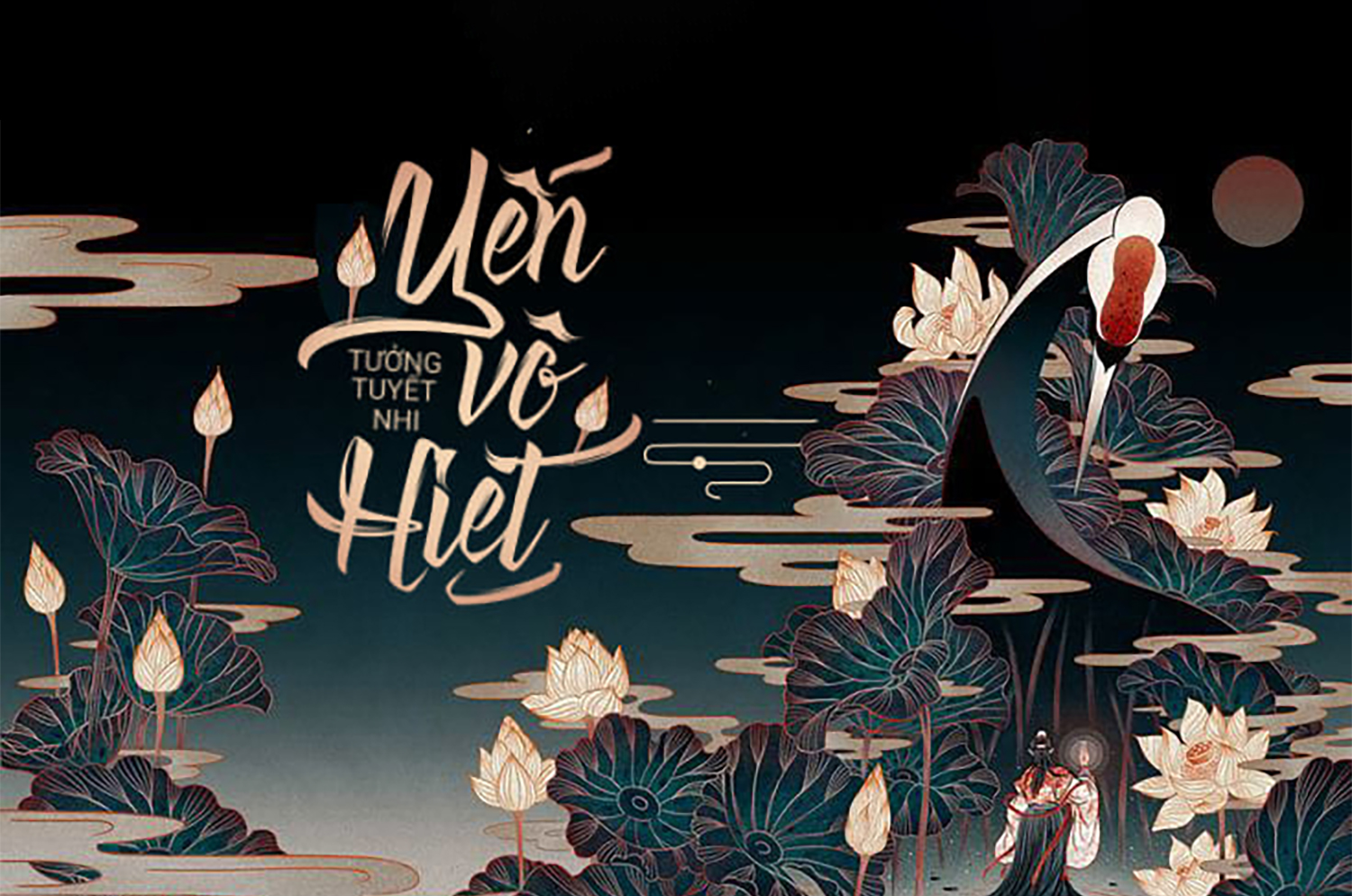
Tải font Absolute Việt Hóa – Phù hợp thiết kế cổ trang Phần Mềm Gốc 10 Tháng 05 năm 2024 0 0 772 Absolute Việt Hóa là bột font chữ rất hợp cho các thiết kế cổ trang, font đã được Việt Hóa đầy đủ với các dấu được thiết kế rất kỹ lưỡng rồi nhé. Tải font Absolute Việt Hóa – Phù hợp thiết kế cổ trangPass Giải Nén: phanmemgoc.vnBài viết liên quan: Tải trọn bộ font Philosopher Việt hóa (4 font) 10 Tháng 05 năm 2024 Font DT Phudu – Font chữ phong cách xưa cũ 10 Tháng 05 năm 2024 Font Valky Việt hóa v2 – Kiểu font hiện đại, cổ điển 10 Tháng 05 năm 2024